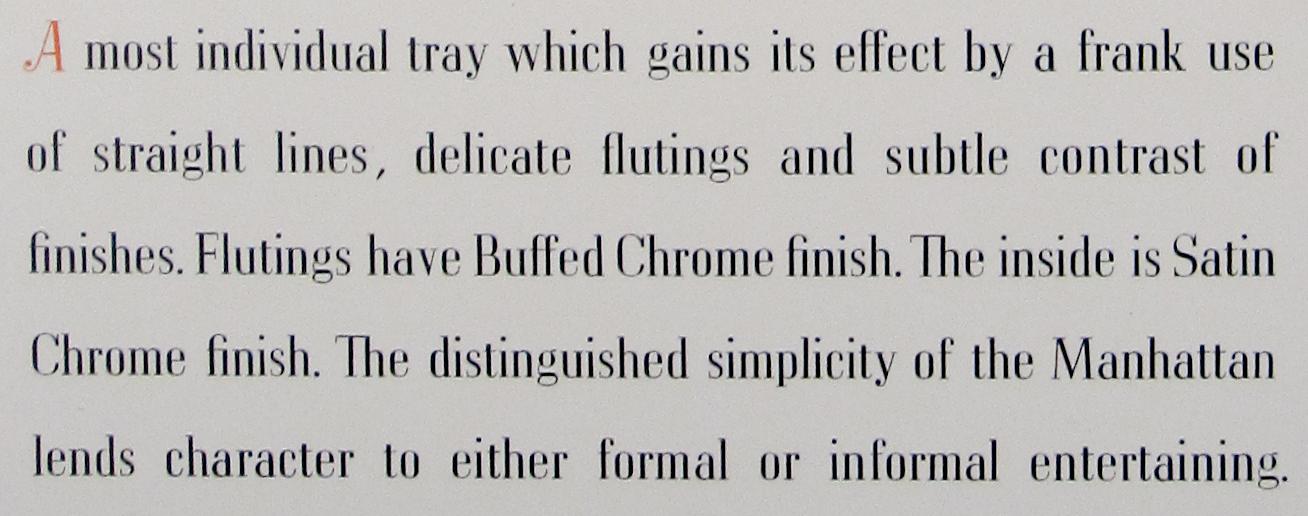
Wer kennt diese Schrift?
Ich bin auf der Suche nach dieser Schrift. Eine schmal laufende klassizistische Antiqua mit alternativen Swash-Lettern. Das kleine "k" ist wohl besonders charakteristisch. Wäre für Infos und Anregungen sehr dankbar.
Jetzt habe ich es wohl doch noch herausgefunden. Es müsste die Corvinus sein. Von Imre Reiner aus dem Jahr 1954. Falls es noch jemanden interessiert ;-)